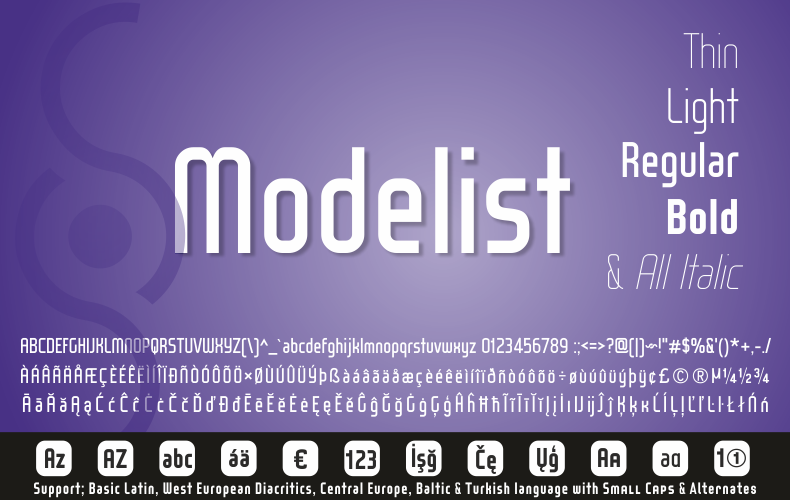
Wox Modelist Font Family – Download Grátis
Esta é uma demo versão do Wox Modelist Font Family, uma família de fontes sans serif criada pelo Studio Typo. Com seu design limpo e moderno, a Wox Modelist é perfeita para criar gráficos profissionais que buscam um equilíbrio entre simplicidade e expressividade. Com seus 50 caracteres básicos em nossa demo, você pode experimentar as diferentes formas e estilos desta família de fontes. O Studio Typo criou uma experiência sólida para quem deseja explorar a Wox Modelist antes de considerar seu uso comercial. Visite o site www.studiotypo.com para obter mais informações e conhecer suas opções completas. Além disso, a Wox Modelist proporciona um layout elegante, que se adequa perfeitamente a sites profissionais, design gráfico, publicidade digital ou qualquer projeto onde você deseja destacar seu texto de uma maneira clara e moderna.